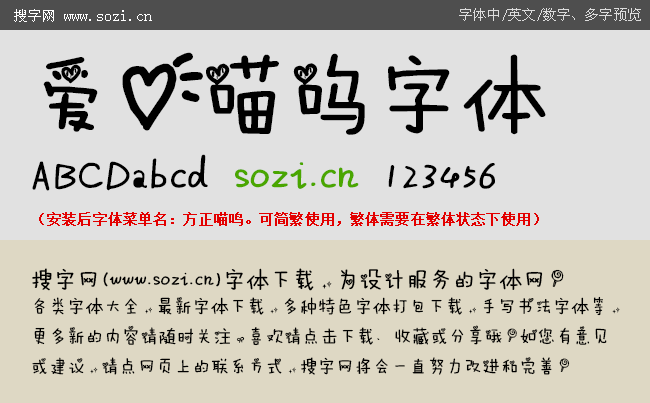
愛心喵嗚字體(FZMM)
搜字網給大家提供一款很卡通的手機中文字體下載。修改者將它命名為心心喵嗚中文字體,這款手機字體是以方正喵嗚體為原形,字體的一些筆畫替換成了非常有趣的卡通心形圖案,方正喵嗚體是少女漫畫家喵嗚聯手方正出品的一款手寫涂鴉字體,字形活潑、可愛、隨意,給人一種無憂無慮毫無約束的自由之感。特別適合喜歡手機字體個性一些的朋友在手機上安裝使用。